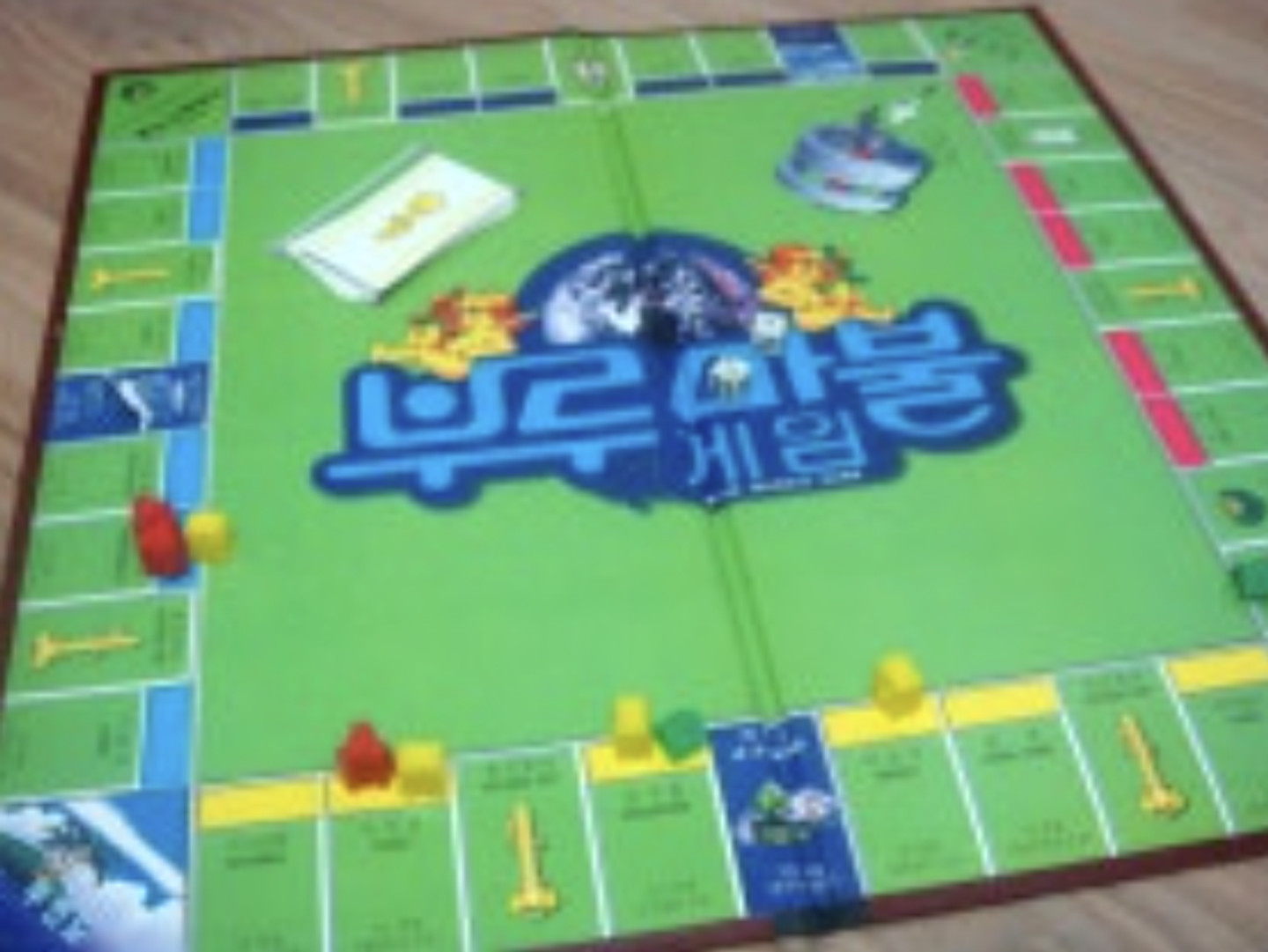
이 부루마불 글씨체 좀 알려주세요.... 일주일째 못찾는중
폰트 아님
폰트 아닌 그냥 레터링입니다.
과거에는 다 손으로 그렸습니다.
요즘은 컴퓨터로 서체를 변형해서 사용하지만 저 당시에는 작도기등으로 어렵게 만드는게 로고였습니다. 서체라는 개념도 희미했던시절이였죠. 이미지올린걸 보시면 과거부터 로고서체가 그대로입니다.(컬러와 스타일만 바뀌고요) 부루마블이 회사 서체를 따로 개발하지 않을테니 일러스트레이터등으로 따서 만드시는게 좋겠습니다. 아니면 서체를 개발해서 부루마블에 팔아보세요